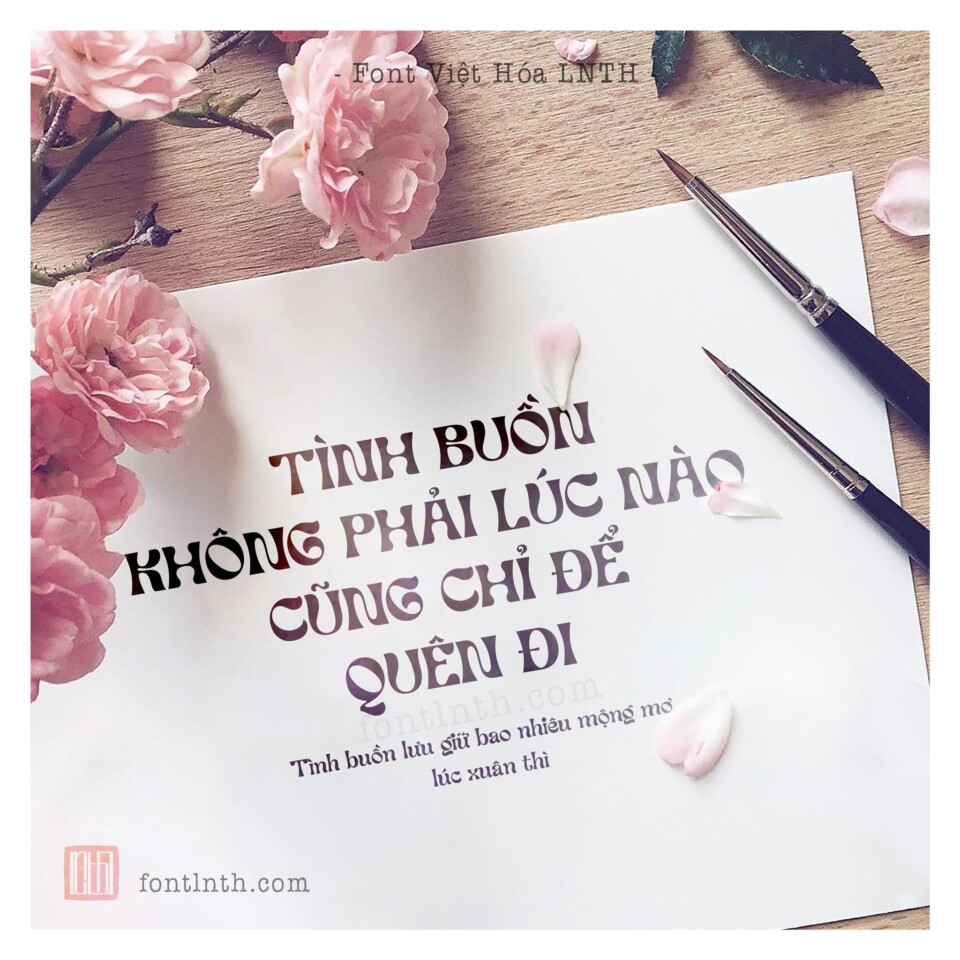
Giới thiệu về Font việt hóa LNTH Guyon Gazebo
Trong thế giới đồ họa hiện đại, việc tìm kiếm một bộ Font Chữ vừa mang nét cổ điển vừa giữ được sự sang trọng là điều vô cùng cần thiết. Font việt hóa LNTH Guyon Gazebo chính là sự lựa chọn hoàn hảo cho những ai yêu thích phong cách Serif truyền thống nhưng vẫn muốn có chút đột phá mới lạ. Bộ font này được đội ngũ LNTH trau chuốt tỉ mỉ từng đường nét, giúp các ký tự tiếng Việt trở nên hài hòa và không lỗi dấu khi sử dụng trên các phần mềm thiết kế phổ biến hiện nay.
Đặc điểm nổi bật của Guyon Gazebo
Guyon Gazebo sở hữu những đường chân chữ mạnh mẽ, rõ ràng cùng độ tương phản giữa các nét thanh và nét đậm một cách tinh tế. Điều này giúp bộ chữ có khả năng hiển thị tốt trên cả nền tảng in ấn lẫn kỹ thuật số. Khi được Việt hóa, các dấu thanh được đặt ở vị trí tối ưu, giữ nguyên được linh hồn và cấu trúc gốc của tác giả. Đây là công cụ đắc lực để các bạn học sinh, sinh viên hay các thầy cô giáo sử dụng trong việc thiết kế slide bài giảng, thiệp mời hoặc các tài liệu học tập cần sự trang trọng.
Ứng dụng của Font việt hóa LNTH Guyon Gazebo trong học tập
Nhờ vào vẻ ngoài lịch lãm, Font việt hóa LNTH Guyon Gazebo thường được ứng dụng trong các tiêu đề lớn của báo cáo, bìa sách hoặc các dự án truyền thông giáo dục. Sự rõ ràng của bộ font này giúp người đọc dễ dàng tiếp nhận thông tin mà không bị mỏi mắt. Ngoài ra, tính thẩm mỹ cao của nó còn giúp khơi nguồn cảm hứng sáng tạo cho những người mới bắt đầu làm quen với nghệ thuật sắp chữ Typography.
Kết luận về bộ font độc đáo này